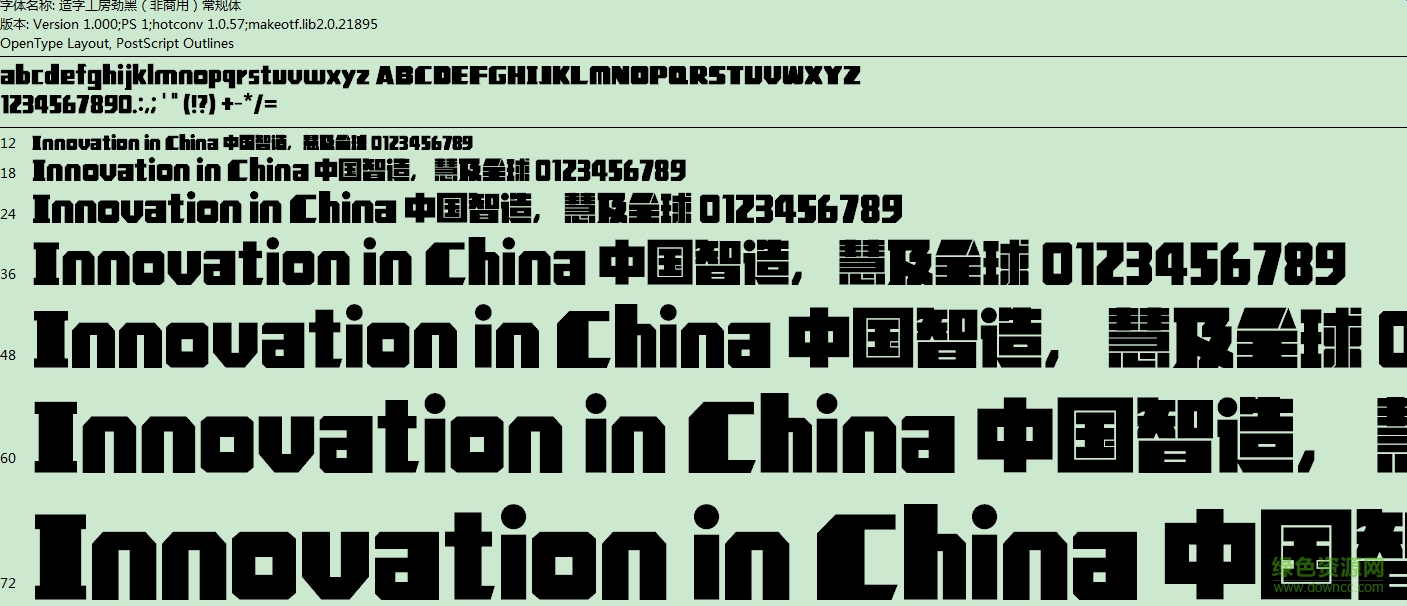
造字工房勁黑體
造字工房勁黑體是一款造字工房出品的字體,用途廣泛。適用于廣告藝術(shù)設(shè)計(jì)、海報(bào)設(shè)計(jì)等方面,小編為大家提供免費(fèi)下載地址。歡迎大家來綠色資源網(wǎng)踴躍下載哦!
造字工房勁黑體,字形非常有勁,流暢,字體工整??梢杂糜谂虐嬗∷⒌确矫妫猛緩V泛。字體愛好者們可以來看看。